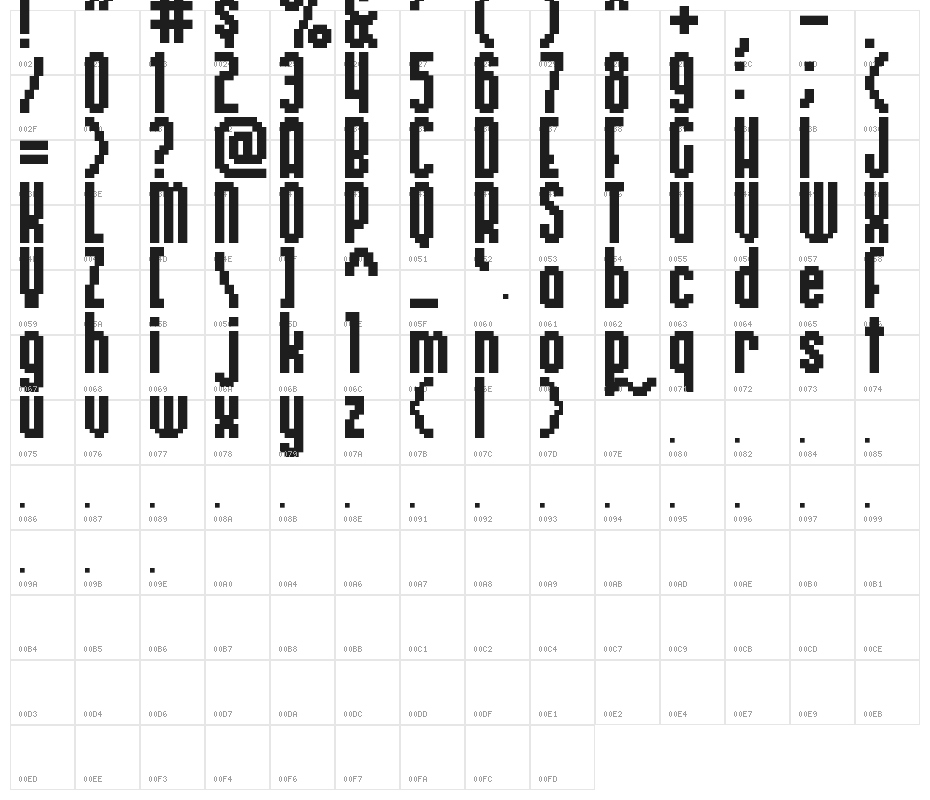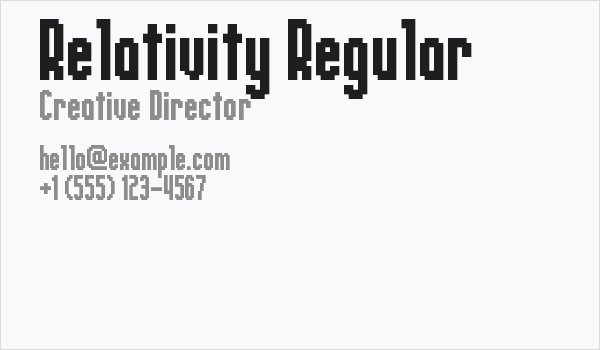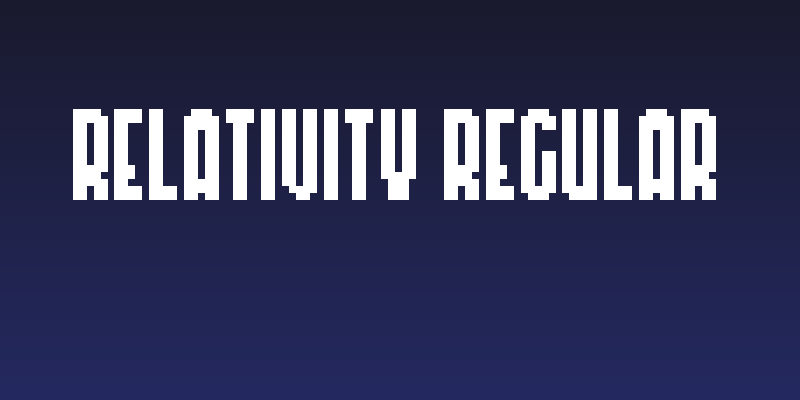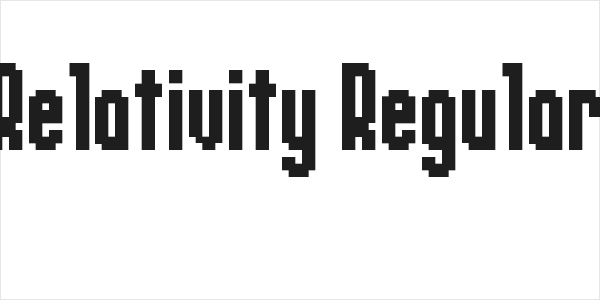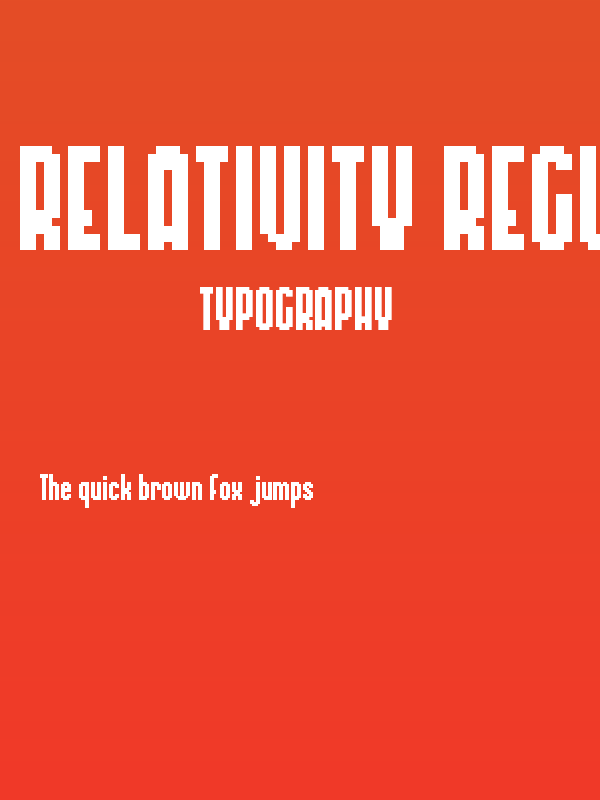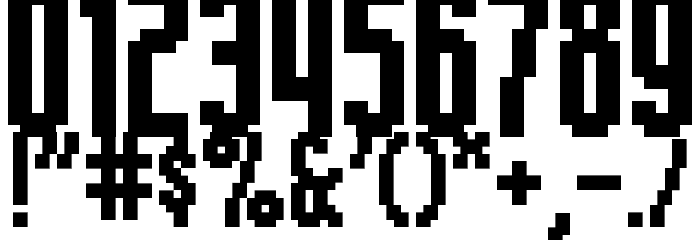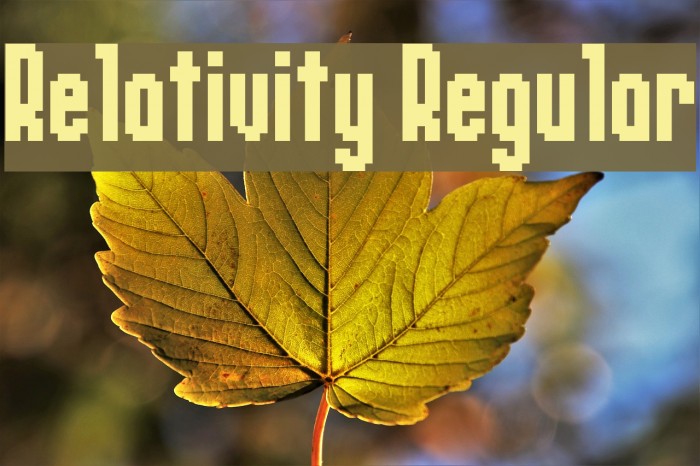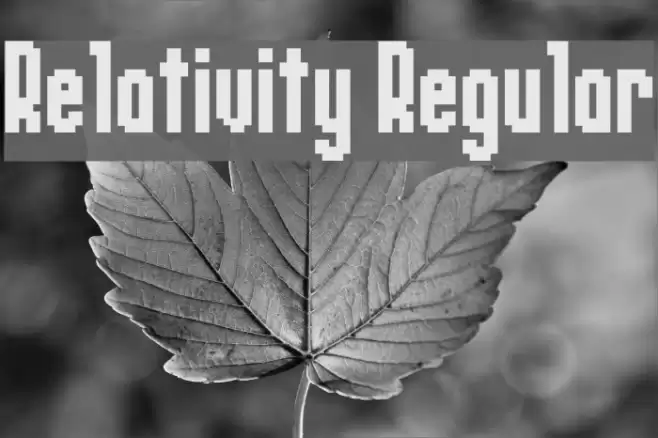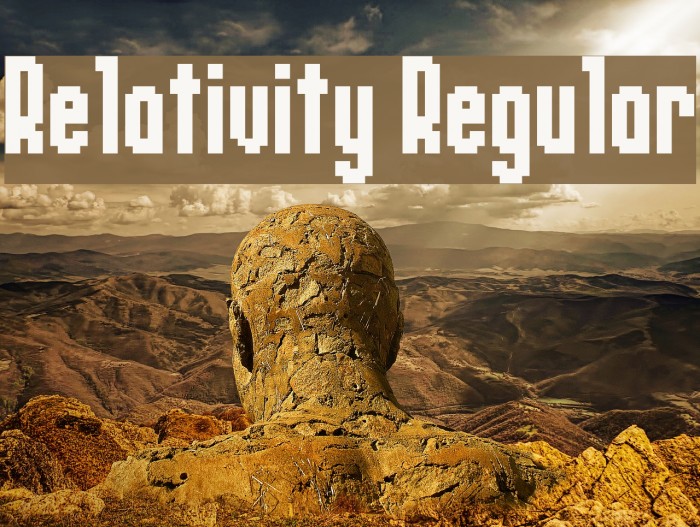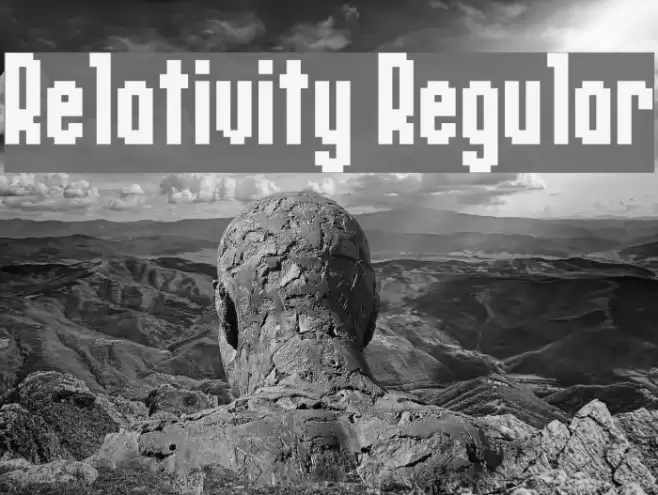
Relativity Regular Font
✎ Pixel
| Catégories | Pixel |
| Style général | Retro, Digital |
| Projets proposés | Ideal for video game design, tech-themed posters, digital art, and retro-style branding. |